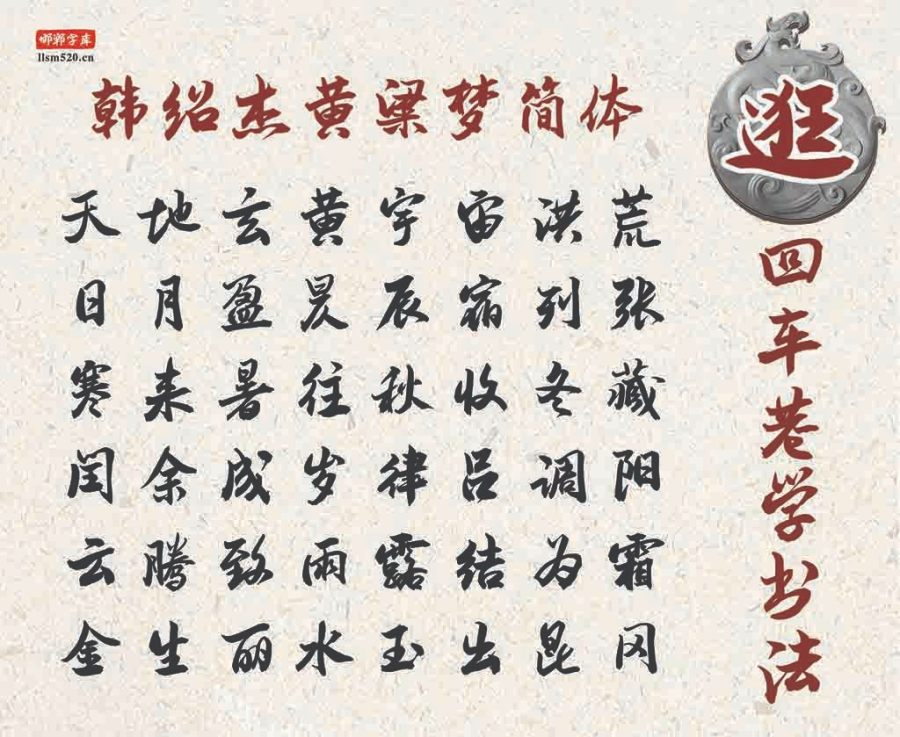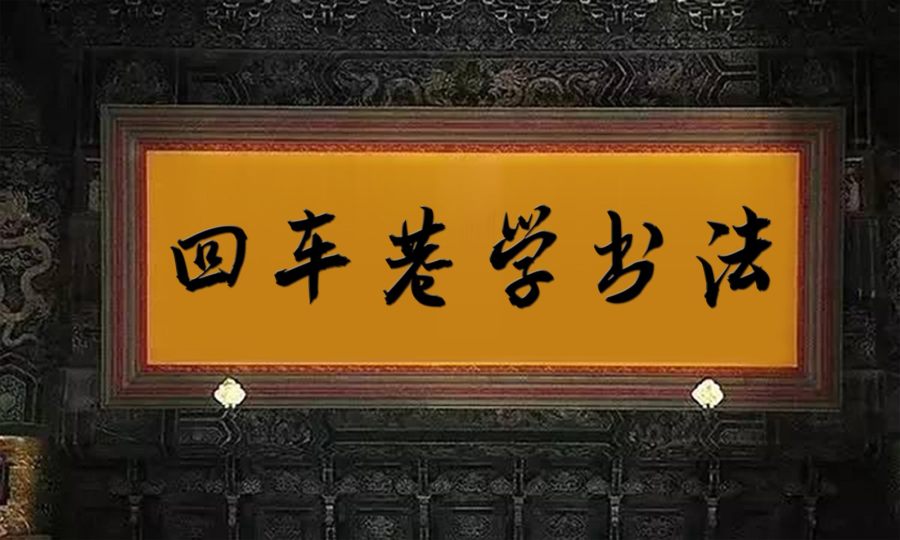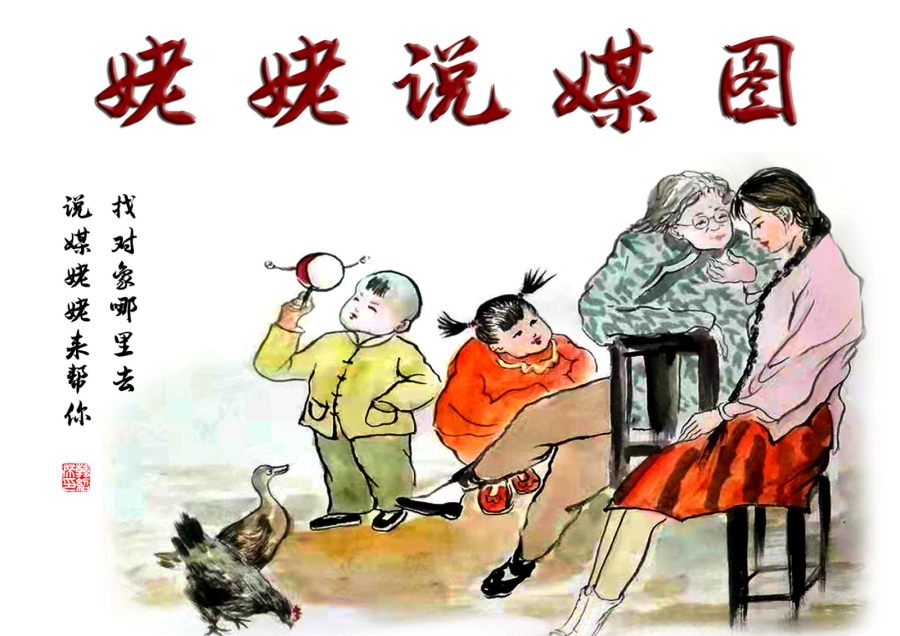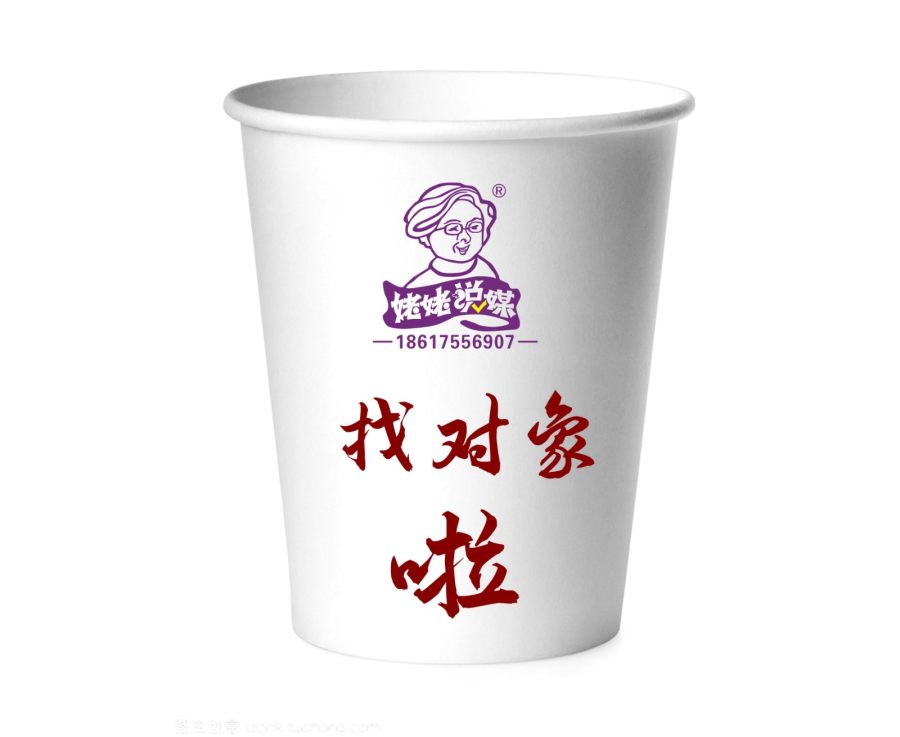
韩绍杰黄粱梦简体以邯郸体创始人韩绍杰老师书写的毛笔字创作而成,韩老师习字四十余载,融会米芾、苏体及行楷,自成风格。现将字体数字化,服务于全国网民大众,让邯郸文化得以流传。
韩绍杰黄粱梦简体字体用笔灵动多变,爽利中见力量,飞白劲健而又沉着,起收笔、提按、 顿挫随心所欲,姿态飞动,中侧锋并用,变化莫测,"风樯阵马 ,沉着痛快”,自称"八面出锋”,体势多欹侧,章法疏密相间。属于书法大字榜书范畴,适用于书籍的封面,以及品牌广告和产品包装设计尤其适合做古籍牌匾用字。